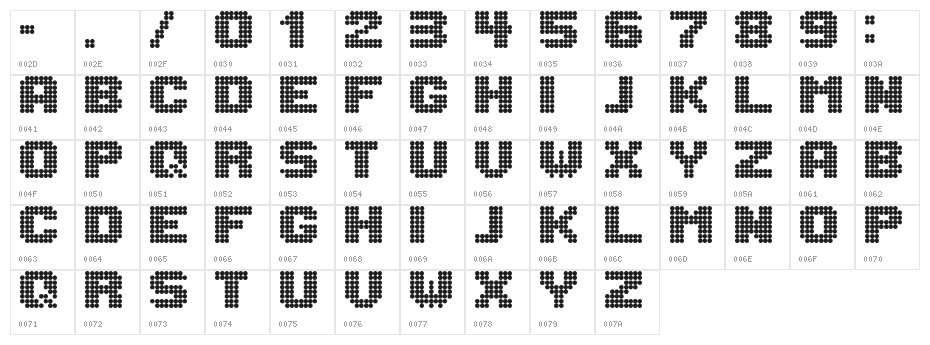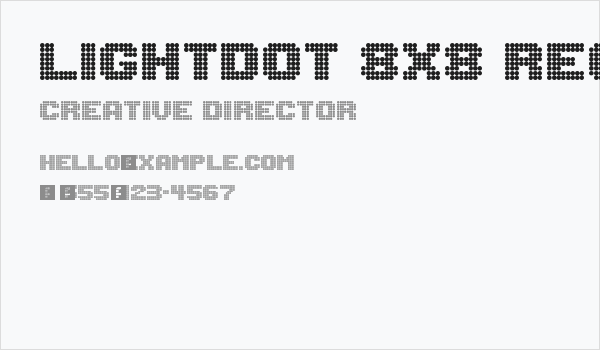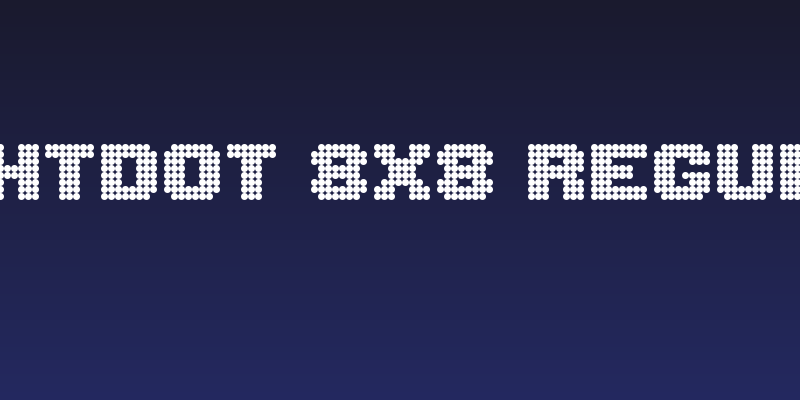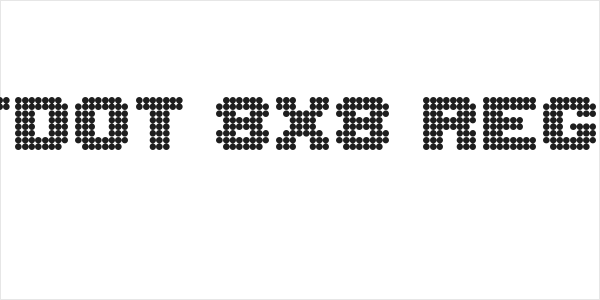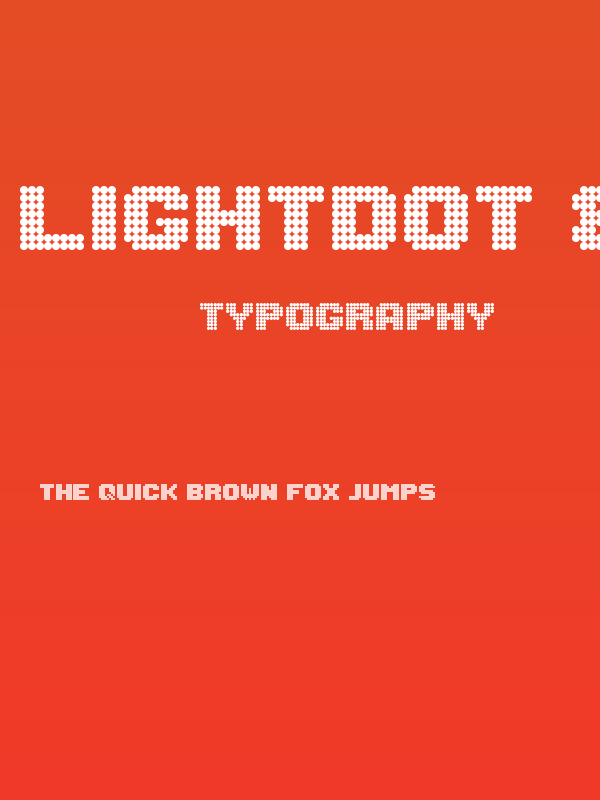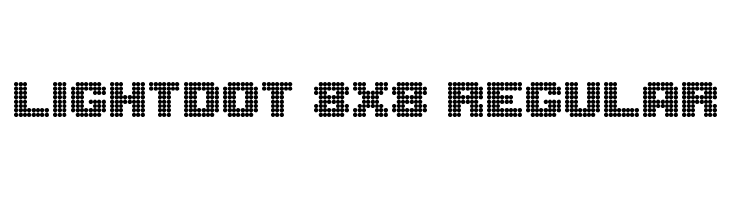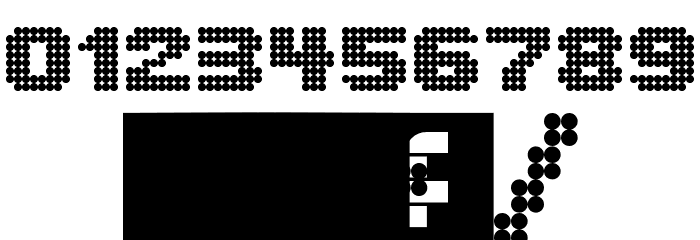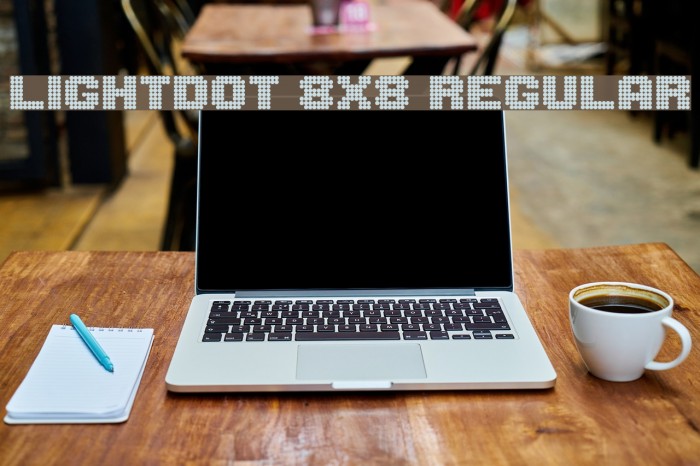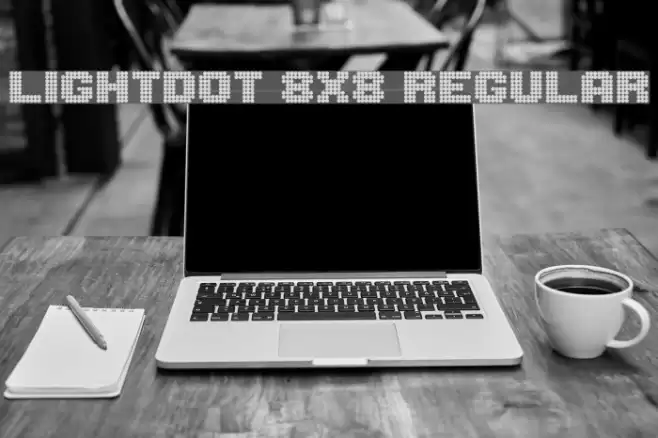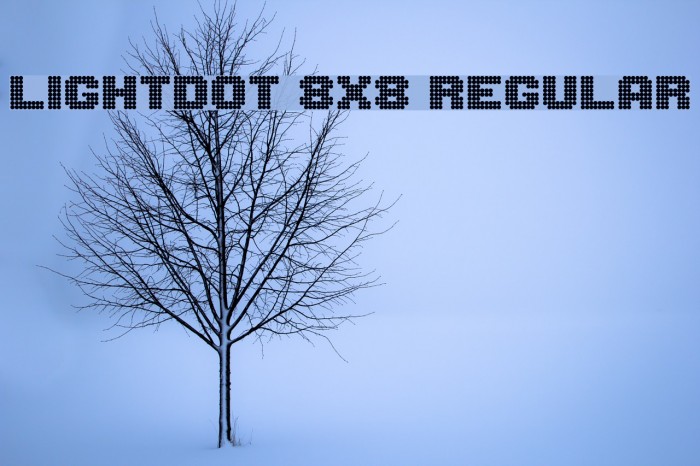
Lightdot 8x8 Regular Font
| समग्र शैली | Modern, Retro |
| उपयोग का मामला | Headlines, Logos, Digital Displays |
| सुझाए गए प्रोजेक्ट | Ideal for digital-themed designs, tech-related branding, retro gaming interfaces, and creative posters. |